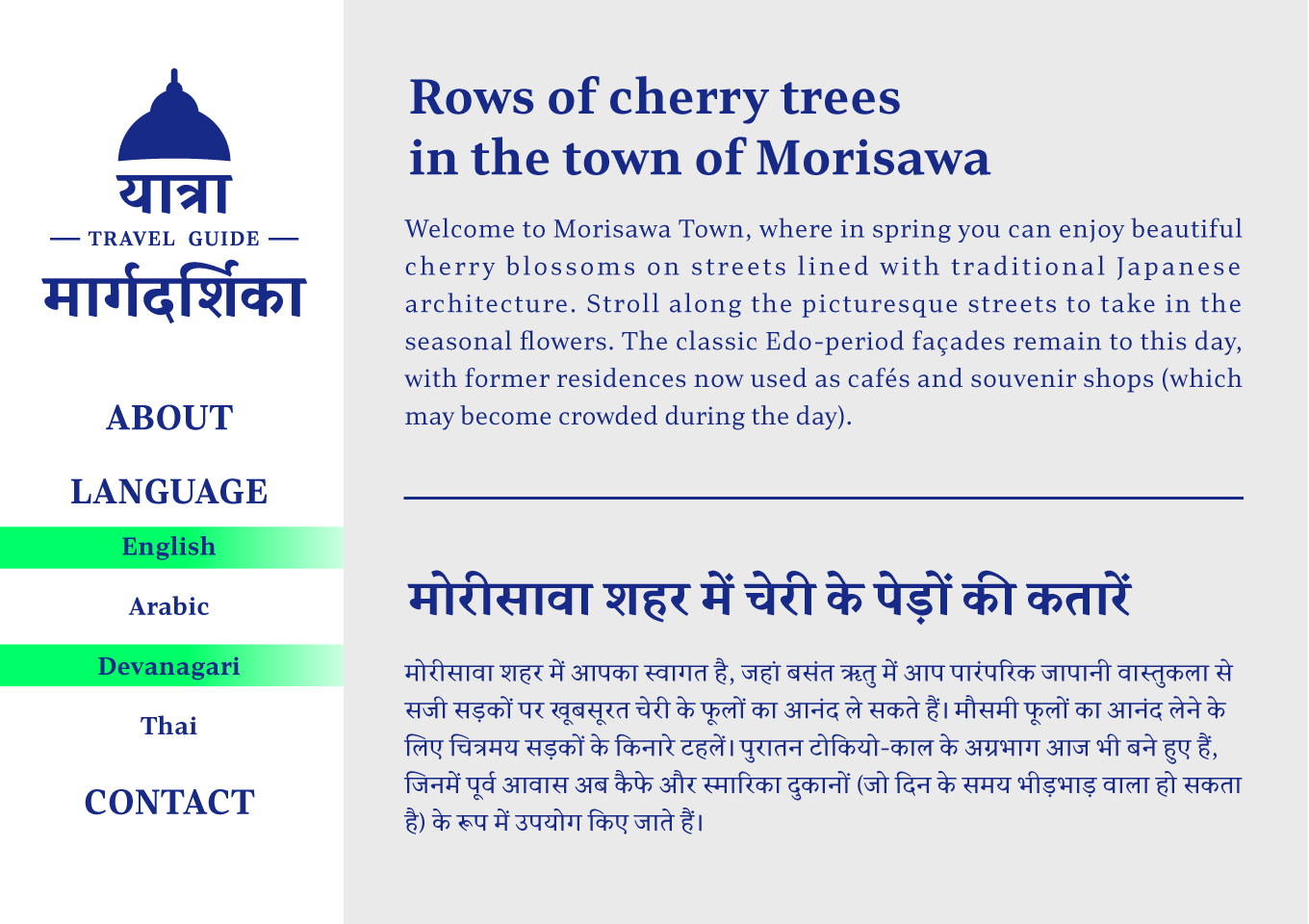
「Lutes UD Devanagari」は欧文フォント「Lutes UD PE」の多言語展開として作成されたデーヴァナーガリー文字のフォントです。デジタルデバイス上での視認性に配慮した、ローコントラストでありながらもクリアですっきりとした印象のセリフ書体「Lutes UD PE」の特徴を反映しています。マラティー語・ネパール語の異体字を搭載しているため、豊富な言語サポートを実現します。さらに伝統的なサンスクリット語にも対応する縦型の合字も多数採用しており、高度な組版が可能です。